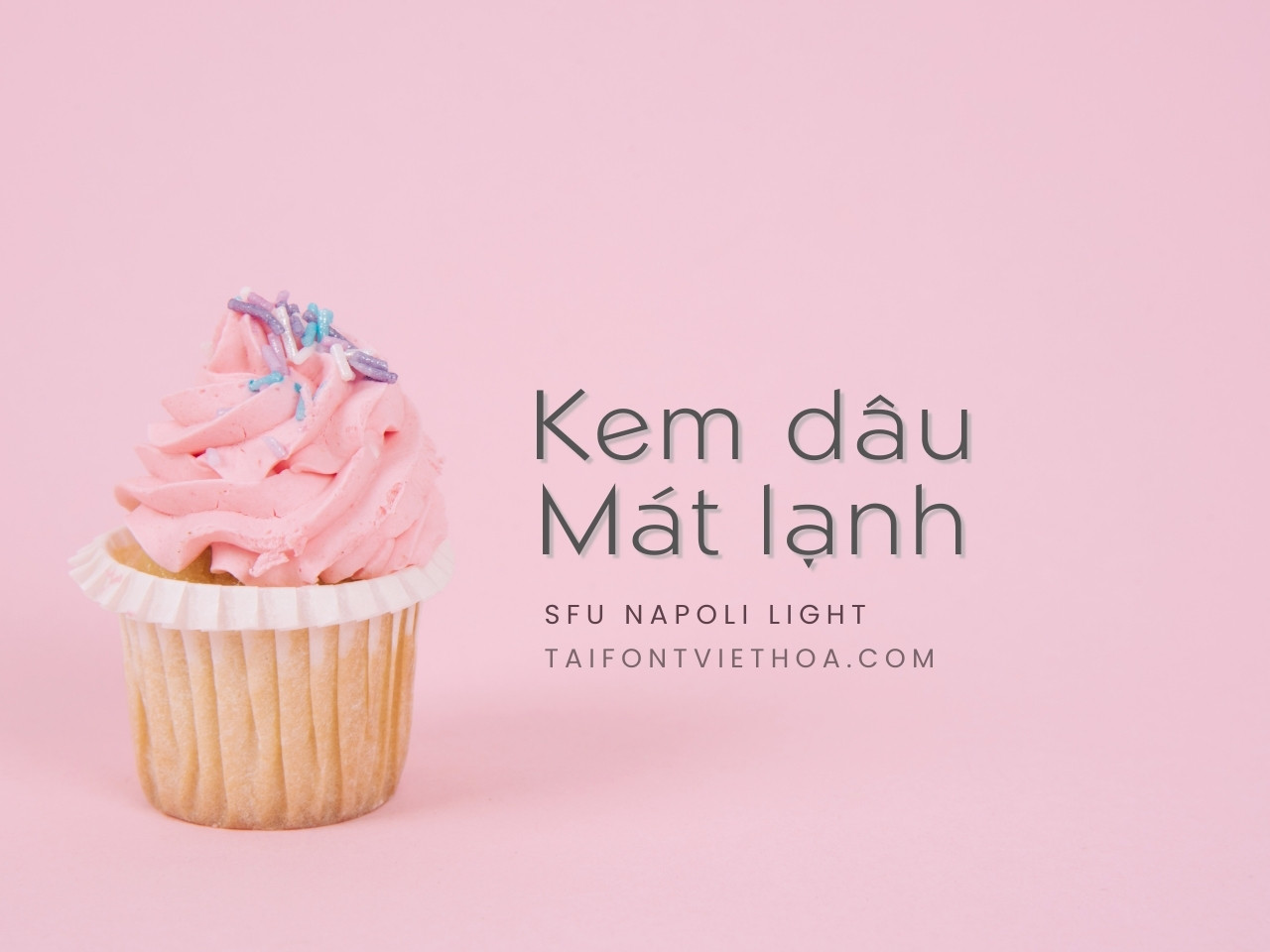
Font việt hóa SFU Napoli
Giới thiệu về SFU Napoli – Thiết kế cổ điển mạnh mẽ
SFU Napoli là một họ font chữ kiểu sans‑serif mang phong cách cổ điển, được phát triển lần đầu vào năm 2006 dưới tên “SFU Napoli Light”, tạo bởi Fontographer và xuất bản trên Fontke etc. Phiên bản gốc gồm nhiều biến thể như Light, Regular, Bold, DemiBold với tổng số khoảng 385 ký tự. Mặc dù nguồn gốc chính xác của tác giả chưa rõ, font này gây ấn tượng mạnh nhờ cấu trúc chữ rộng rãi, thẳng nét, phù hợp với nhu cầu thiết kế retro và công nghiệp.
Mô tả thiết kế & ứng dụng của SFU Napoli
SFU Napoli thuộc dạng sans‑serif hiển thị (display)với cấu trúc chữ khỏe khoắn, độ tương phản thấp, nét thanh rắn tay cọ, phù hợp với thiết kế mạnh mẽ. Các chữ như “O”, “P” bo tròn đều, trong khi các chữ “N”, “A” giữ góc cạnh sắc nét, tạo cảm giác cân bằng giữa nghiêm túc và mềm mại.
Phiên bản Light có độ dày trung bình-mỏng, dễ dùng cho tiêu đề, logo, poster, bao bì. Biến thể Bold/DemiBold tăng khả năng nhận diện khi cần tạo dấu ấn mạnh mẽ.
Nếu xét yếu tố kỹ thuật, SFU Napoli hỗ trợ ligatures cơ bản của sans‑serif, nhưng không tích hợp ligatures trang trí như script hoặc calligraphy. Độ dãn ký tự tốt, có thể điều chỉnh kerning dễ dàng trong các phần mềm như Illustrator, Photoshop, InDesign.
Ứng dụng phù hợp:Thiết kế logo, bảng hiệu, poster, bao bì sản phẩm mang phong cách cổ điển, nhìn khỏe, mạnh mẽ; thiết kế banner quảng cáo, tiêu đề web, tạp chí; mockup jersey thể thao,…
Ngành nghề phù hợp:Thương hiệu & marketing, ẩm thực (nhà hàng phong cách retro), agency quảng cáo, sản xuất – công nghiệp, thể thao & giải trí, thiết kế packaging.